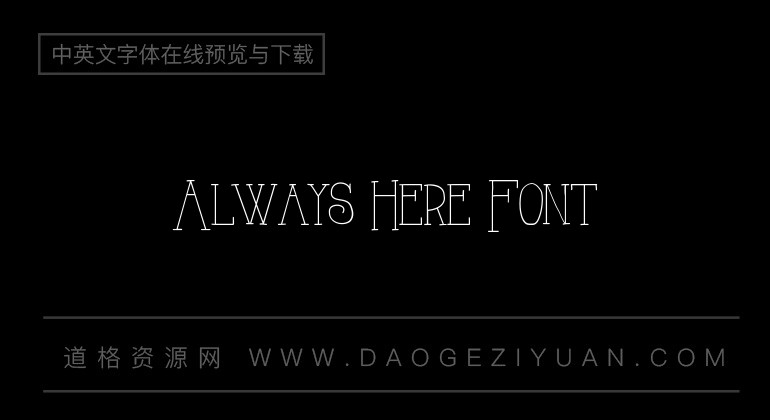
Always Here Font 是一种免费的手写风格字体,常用于卡片,海报,广告,书籍封面等设计项目。此字体具有流畅的曲线和自然的笔画,使其看起来非常适合用于手写或手绘主题的设计中。它包含大写字母,小写字母,数字和标点符号,使其非常适合用于各种类型的设计项目。Always Here Font 是一种免费的字体,并且可以在许多不同的网站上进行下载。内容介绍
Always Here Font是一款非常不错的手写艺术字体,具有很好的视觉感,适合于文化类的宣传设计、商业类品牌的广告和产品包装设计以及个性化文字排版等较多场景。